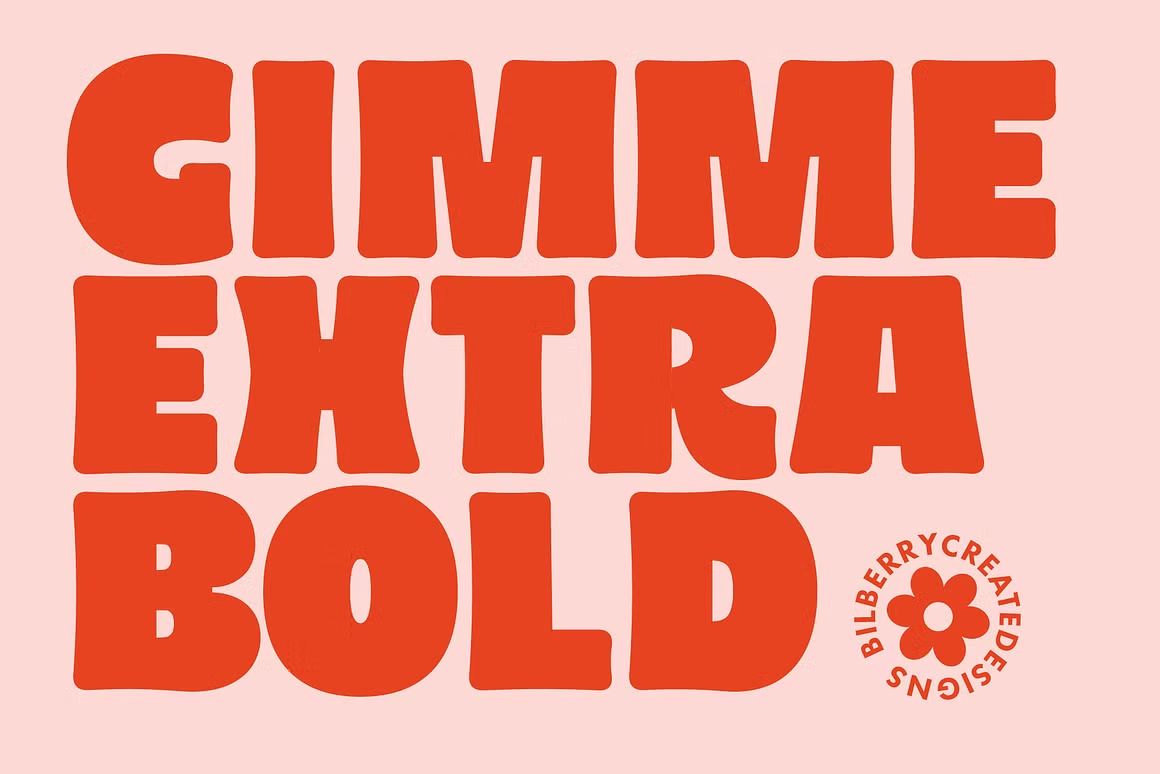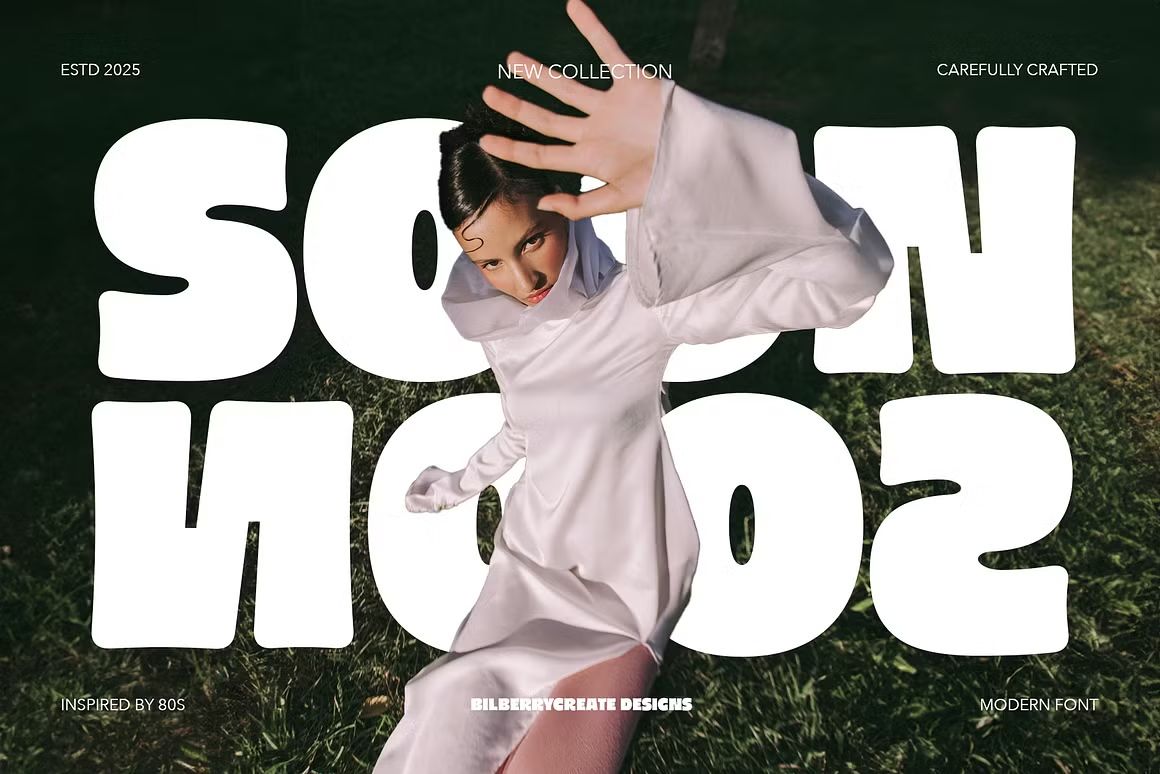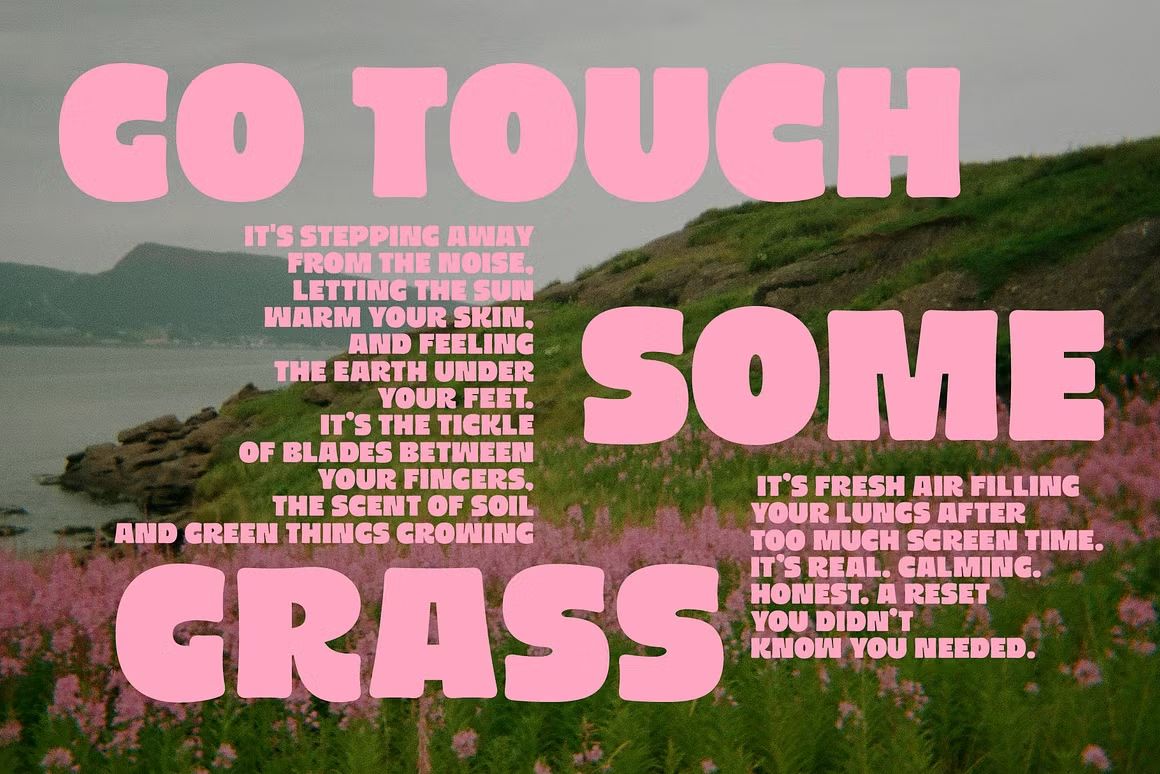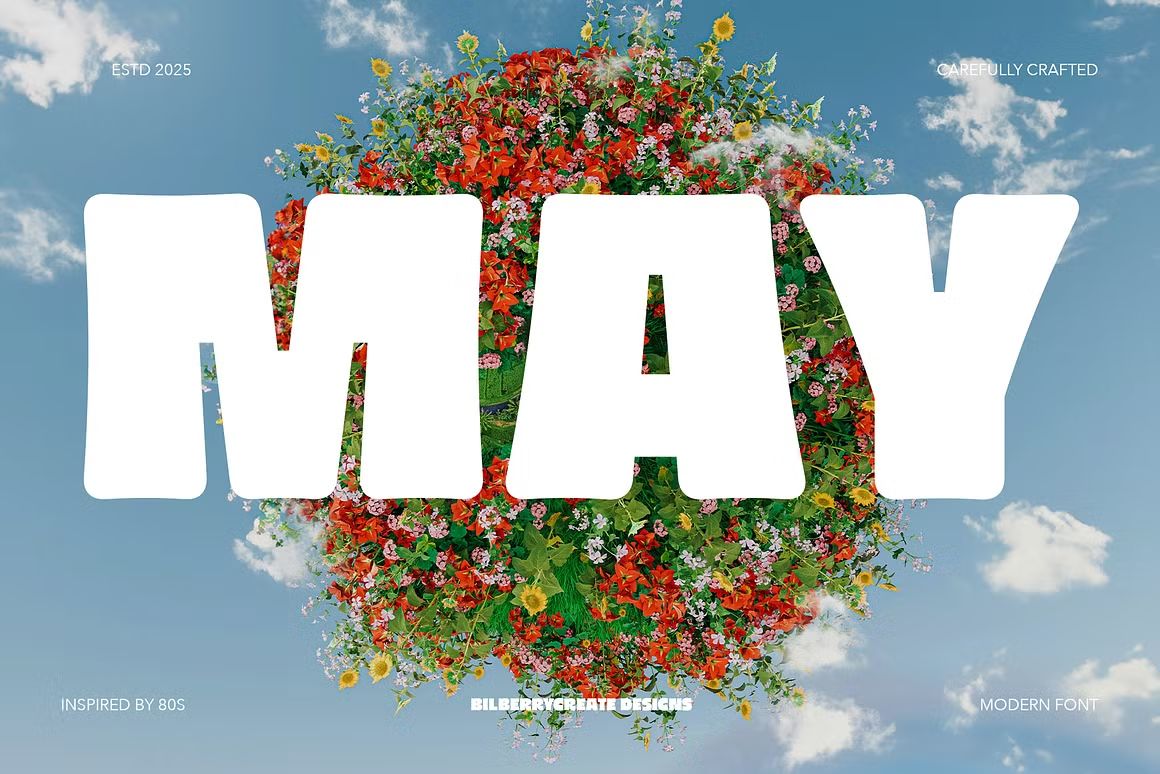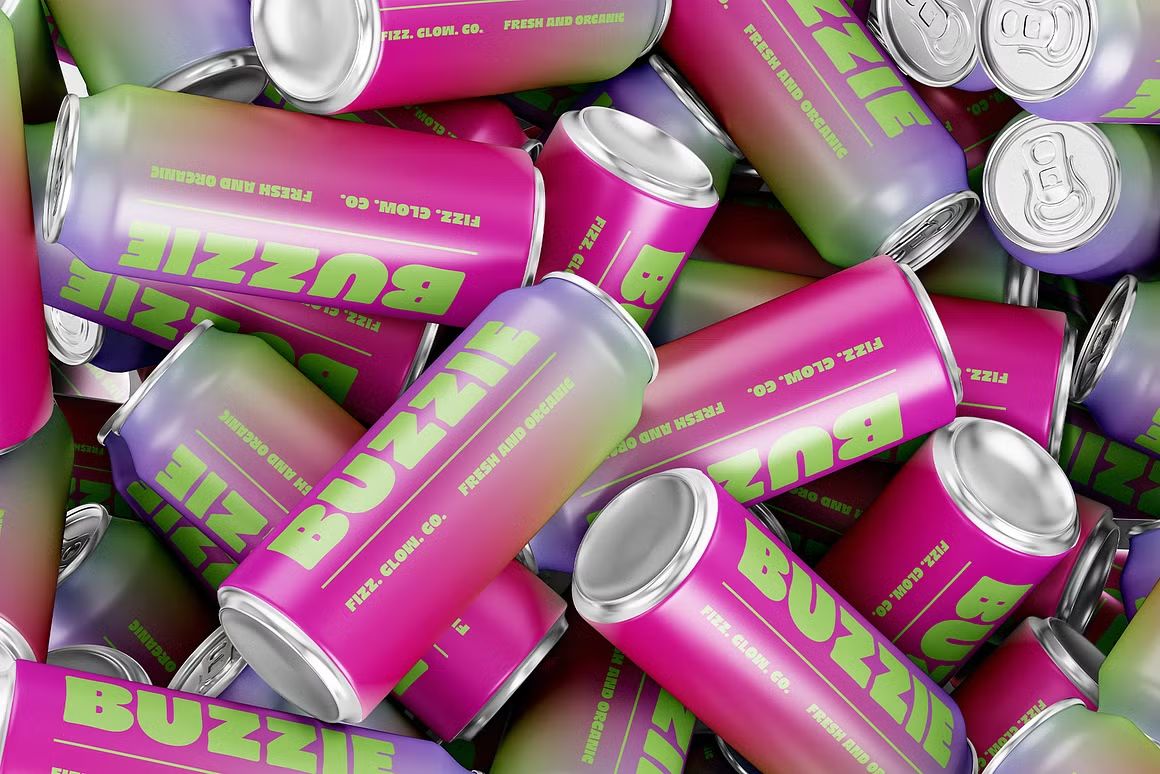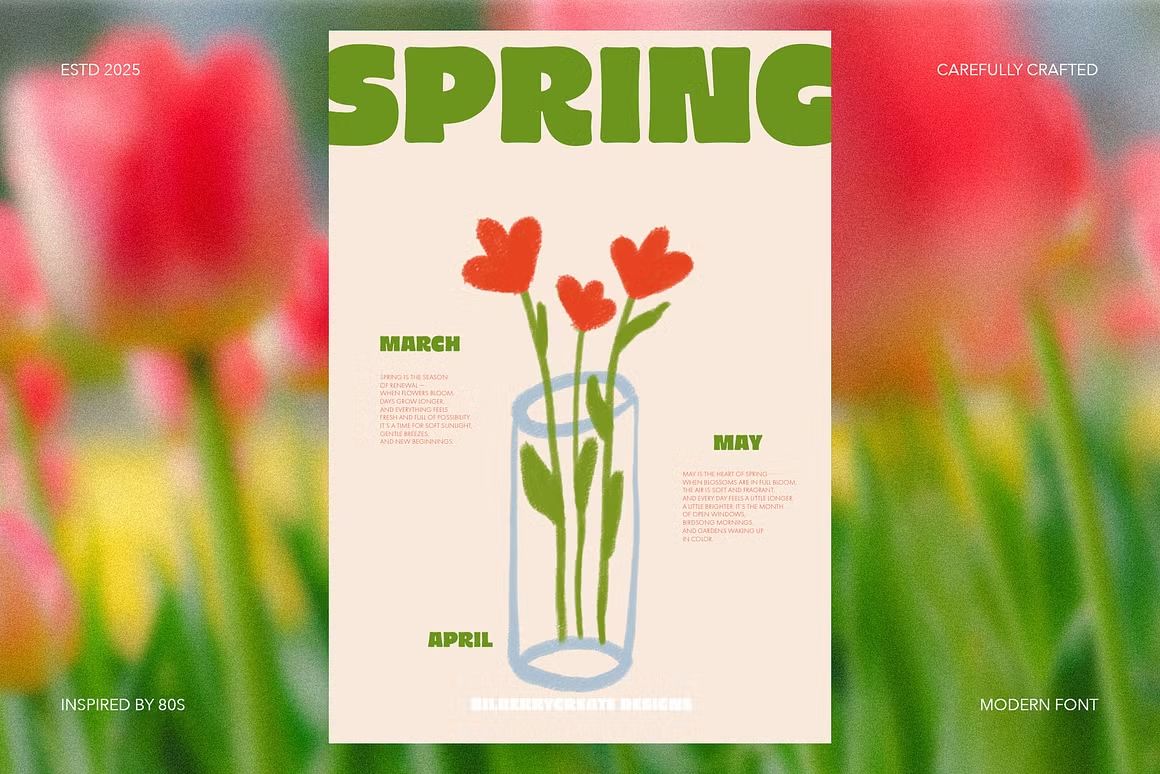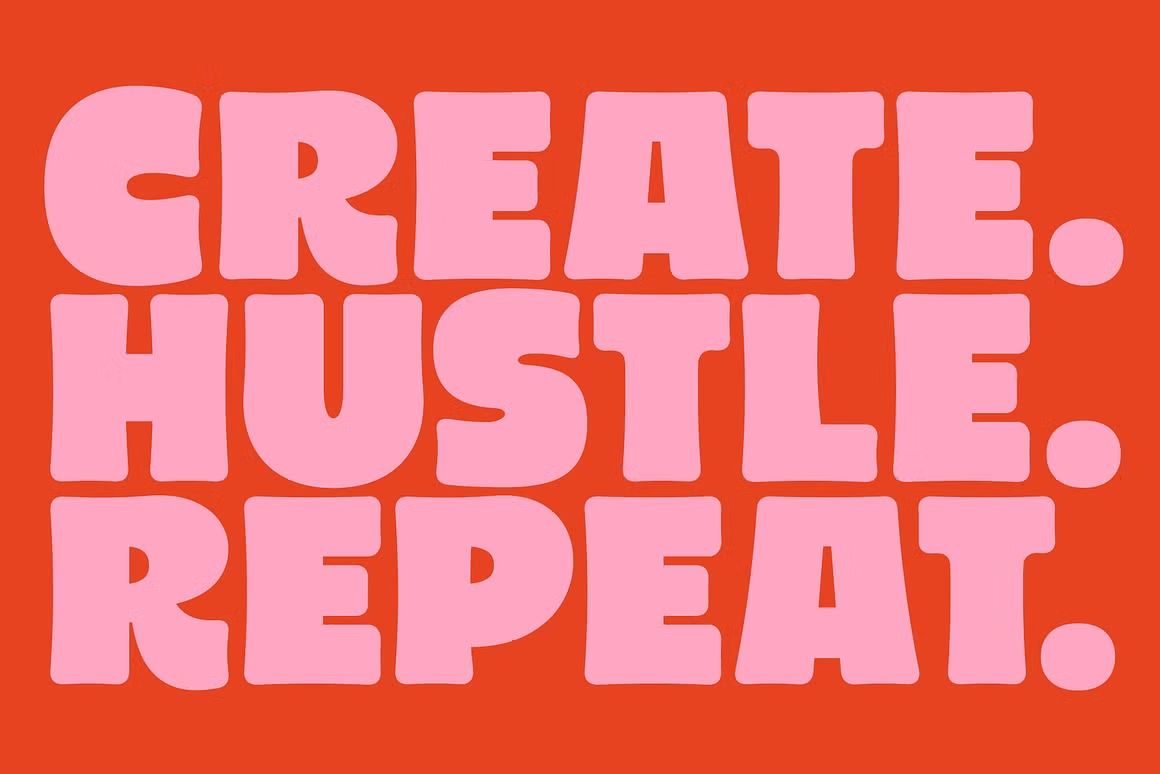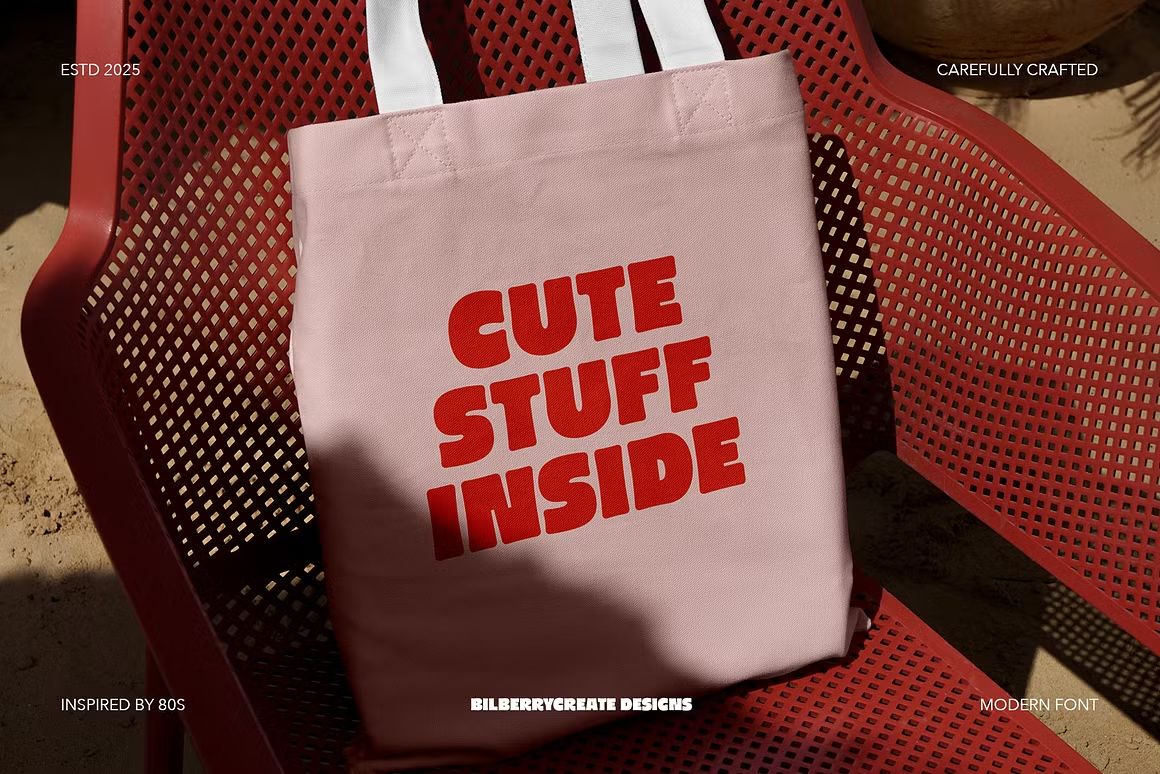
Gimme Extra Bold – Sans Serif
Gimme Extra Bold adalah font sans serif modern dan tebal, sempurna untuk headline, branding, dan desain mencolok. Format OTF/TTF/WOFF, siap digunakan di berbagai proyek.
Gimme Extra Bold adalah font sans serif tebal dan modern yang dirancang untuk menarik perhatian dengan gaya yang kuat dan percaya diri. Cocok untuk headline, poster, branding, kemasan produk, dan desain digital yang membutuhkan tipografi mencolok. Dengan bentuk huruf yang bersih, proporsional, dan serbaguna, font ini memberikan kesan profesional sekaligus energik dalam berbagai konteks visual.
• Gaya sans serif tebal, ideal untuk judul dan branding
• Tampilan kuat, bersih, dan mudah dibaca
• Termasuk huruf kapital, angka, dan simbol